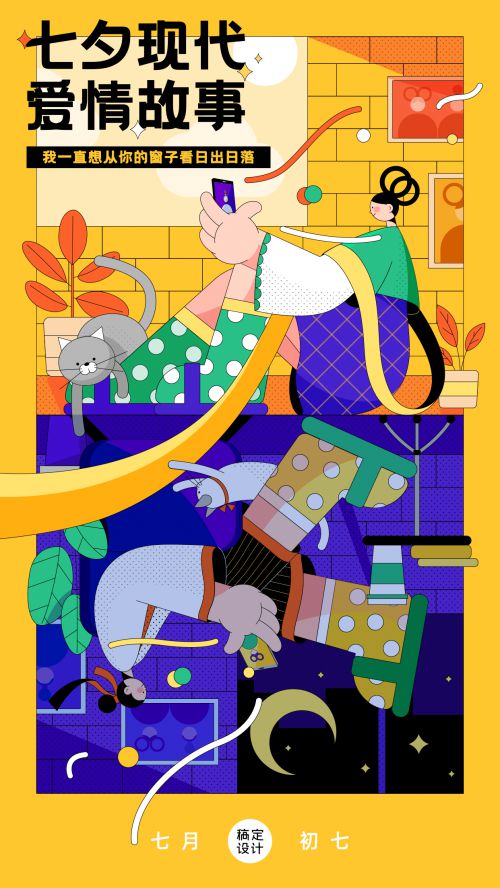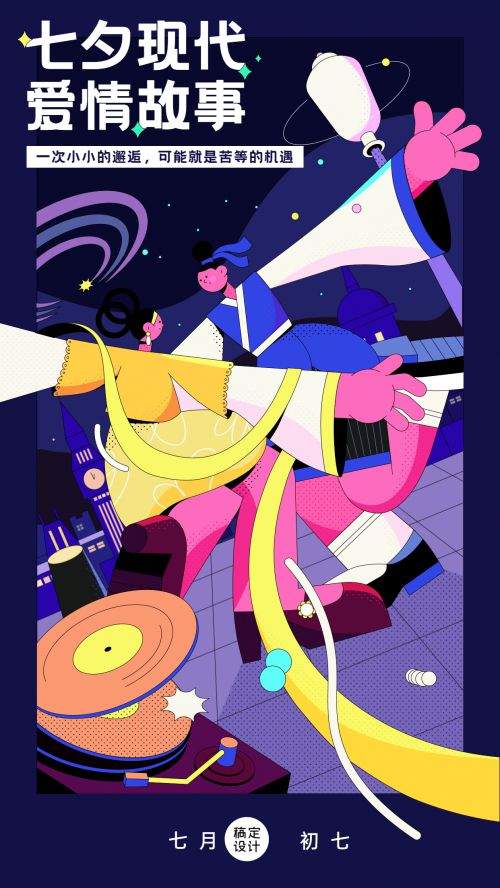
字由文艺黑是字由品牌推出的创意黑体字体,以现代简约风格为核心,将图形设计法则巧妙融入黑体设计。字体字形方正饱满,重心居中且中宫适中,既保留黑体的稳重基调,又通过优雅的艺术弧线处理增强视觉张力,让整体结构充满平衡感与力量感。 字由文艺黑笔型设计独具特色,以利落直角勾勒轮廓,搭配方头笔画与均匀粗细,笔画连接采用断开处理,既保持线条的独立性,又让字形更显灵动透气。作为免费商用字体,字由文艺黑字符集覆盖常规中文,适用于海报设计、品牌视觉、新媒体排版等多元场景,兼顾艺术性与实用性,是现代设计中追求文艺感与商业价值的理想选择。